Готический шрифт. Пошаговые уроки. Прописные буквы
Это завершающий урок серии пошаговых уроков по готическому шрифту. Если вы овладели строчными буквами из предыдущих уроков, то научиться писать прописные будет довольно просто.
Удобно, что все буквы готического алфавита строятся из одинаковых элементов. Изучив одну букву вам будет легче писать остальные.
Полезная информация о прописных буквах готического шрифта
В готике есть много разновидностей прописных букв. Смотрите больше примеров, отмечайте и запоминайте особенности. Создайте свою коллекцию прописных букв. После того, как изучите основы, вы сможете комбинировать и импровизировать с различными элементами, адаптируя их под конкретный проект.
Как правило прописные буквы значительно выступают за пределы строки вверх и вниз, в отличие от строчных.
Они занимают квадратную область или даже широкий прямоугольник, а формы их довольно округлые.
Прописные в готическом шрифте так сильно отличаются от строчных, по крайней мере, по двум причинам. Скорее всего они произошли из букв унциального письма и позднего верасльского, которые имеют округлые формы. И конечно, в традиционном письме они облегчали поиск новой строки среди монотонных вертикальных штрихов.
Вторая причина объясняет почему готические прописные так хорошо смотрятся в традиционных цветах: алом, синем или зеленом. Для выделения особо важных абзацев вокруг прописной буквы рисуют золотые рамки или замысловатые узоры. Готическая письменность вообще располагает к экспериментам в прописных буквах, так что, я надеюсь, вы будете получать большое удовольствие от них.
Большие округлые формы прописных букв в готике образуют значительные просветы внутри буквы. Во всех шрифтах эти просветы называются каунтер (англ. counter). В готике принято заполнять внутреннее пространство различными декоративными элементами.
Это могут быть тонкие завитки, ромбики, декоративные штрихи внутри и снаружи буквы. Здесь есть место эксперименту.
Готическое письмо: прописные готические буквы от A до Z.
Наши заглавные буквы имеют высоту шесть ширин пера. Это значит, что если вы пишете пером, шириной 3 мм, то высота буквы будет 18 мм. Чтобы создать нужную сетку для упражнений удобно воспользоваться одним из генераторов сеток, про которые я написал здесь.
Дальше будут инструкции выполнения буквы по штрихам. Каждый новый штрих обозначен красным цветом. Тонкие штрихи рисуются левым уголком кончика пера. Вы просто поворачиваете ручку пера против часовой стрелки и проводите линию левым уголком пера. Так мы уже писали в третьем уроке по строчным буквам.
Основным правилом готического письма является то, что мы всегда ведем пером сверху вниз, либо слева на право. В любом случае перо всегда должно двигаться назад, оставляя за собой штрих.
Если вести пером вперед, то оно будет цепляться за бумагу, издавай жуткий скрежет и оставляя неровный штрих.
Изучение буквы «A», как ни странно, не поможет в изучении остальных букв. Зато, она довольно простая. Здесь приведен довольно нежный вариант буквы. Попробуйте вариацию с одинаковыми ножками. Просто нарисуйте нижнюю ножку правого штриха также плоско, как и первого.
На самом деле, в готическом письме есть много вариаций прописных букв, так что когда освоите эту форму – экспериментируйте.
В этом примере буквы «B» есть прекрасный образец украшения готического письма — это шипы с левой стороны первого вертикального штриха (5 и 6 позиция в последовательности). Я надеюсь, что вы будете часто использовать это украшение в своих буквах. Эти шипы могут иметь разную форму — прямую или изогнутую. Пишите ту, которая вам сейчас больше нравится.
Как нарисовать такой шип: поставьте перо под углом 45º так, чтобы оно слегка касалось первого вертикального штриха буквы и начинайте вести ручку вправо и сразу вниз, образуя таким образом запятую.
Угол пера должен быть всё время 45º. Следите за тем, чтобы нижний кончик этой запятой не выглядывал за границы вертикального штриха.
Буква «C» — первая круглая буква готического алфавита. Первый штрих начинается чуть ниже полной высоты буквы. Сделайте плавный полумесяц сверху слева на право вниз. Начало тонкое в середине расширение и конец опять тонкий. Поднимите перо и вернитесь к линии верхней границы строки. Держите перо под углом 45º и прислоните его левым уголком к кончику полумесяца, проведите ровную вертикальную линию вниз, сделайте маленький хвостик влево, если хотите. Вернитесь опять наверх, поверните перо на бок, чтобы провести тонкую линию вниз рядом с предыдущей. В конце вернитесь наверх, чуть ниже начала буквы, чтобы нарисовать завершающий элемент.
Если у вас это получилось, значит вы готовы к буквам «E», «G», «O», «Q», «T», «U», «V» и «W». Фантастика!
Эта версия «D» выглядит довольно роскошно. Начинайте как «B», а дальше развлекайтесь, рисуя штрих в форме длинного горнолыжного склона.
Старайтесь сильно не выгибать этот штрих вперед.
Буква «E» пишется почти как «C». Завершающий язычок делайте не слишком длинным. С ним легко увлечься и нарисовать длиннее, чем нужно. Да, возможно, вас заинтересует как сделать конец язычка раздвоенным. Поставьте перо под углом 45º и проведите линию вправо, на последнем миллиметре линии просто поверните ручку пера против часовой стрелки так, чтобы правый уголок пера приподнялся, а левый продолжал скользить по бумаге, вытягивая нижний край линии. Раз, и у вас получился раздвоенный язычок!
Получается? Могу сказать, что этот элемент потребует некоторой практики, но в результате у вас всё получится.
Также, скажу, что после завершения линии можно повернуть перо на бок и уголком аккуратно подправить раздвоенный конец так, как вам нужно.
«F» довольно большая буква. Она содержит две черные линии, образующие белую линию между ними. Всё это создает эффектный контраст. Делайте эти линии плавными и слегка изогнутыми.
Избегайте острых углов как в строчных буквах, делайте их более плавными, чтобы буквы смотрелись потрясающе.
«G» совсем простая, в ней даже нет раздвоенного язычка, как в «E».
Надеюсь «H» тоже достаточно понятная, просто повторяйте по схеме. Новый элемент здесь — это флориш сверху буквы. Да, он оканчивается таким же раздвоенным язычком, какой был у «E».
Совет: когда будете рисовать первый вертикальный штрих, постарайтесь сделать небольшой изгиб влево в самом начале. Потом, когда будете присоединять к этому штриху флориш, можно будет продолжить этот изгиб в горизонтальной плоскости. От этого флориш будет смотреться более изящно.
Разобрались с «H»? Довольны результатом? Поздравляю! Теперь вы можете написать «Happy Birthday» готическим шрифтом. Попробуйте скопировать этот пример:
Дальше «I» — прекрасная, простая буква. Следите за пропорциями, чтобы она не была похожа на «J».
Просто следите за тем, чтобы верхний флориш и нижний завиток не выступали более чем на половину ширины самой буквы.
Как видите, верхний флориш и нижний завиток готической буквы «J» выступает за пределы буквы гораздо сильнее, чем в букве «I». Учтите, что «J» сравнительно новая буква в готическом алфавите, ей всего лет триста (для готики это не много). По факту, «J» – это адаптированная «I», по этому делайте верхний и нижний росчерки значительно крупнее, чтобы они отличались.
«K» cтроится похожим образом с «H». Её главная особенность — широкая диагональная ножка. Она должна быть достаточно длинной и изящной, но не должна сильно выступать за пределы буквы, чтобы не касаться соседней буквы в слове.
«L» почти такая же простая, как «I». Не делайте горизонтальные штрихи слишком длинными.
С готической буквой «L» есть интересная история. Обозначение «£» — английский фунт берет свое начало от готической формы прописной «L».
«L» — первая буква латинского слова «librae», что означает «единица веса». Слово «librae» в английском языке употреблялось в значении «фунт», как фунты, шиллинги и пенсы.
Так почему же фунт назвали librae? Ученые предполагают, что по весу 1 фунт пенсов как раз составлял в сумме 1 фунт деньгами. И еще librae — означает Весы в астрологии. И еще от него происходит слово «equilibrium» (равновесие).
Ну что, достаточно мировой истории? Поехали дальше!
Буква «M» довольно высокая и изящная. Постарайтесь не делать слишком широкими её плечи. Делайте их узкими и вытянутыми, как арки окон в готических соборах. Можно подметить множество интересных сходств между готической архитектурой и готической письменностью.
Важное объявление: Вы находитесь на середине пути изучения прописного готического алфавита! Самое время отдохнуть и размяться. Встаньте, потянитесь, потрясите руками, помассируйте их, чтобы снять напряжение. Посмотрите вдаль, чтобы глаза отдохнули. Можно даже вознаградить себя чаем с печеньками.
Готовы? Тогда продолжаем:
Вы будете рады узнать, что «N» – это «H» без шляпы.
В букве «О» главное получить плавный сбалансированный контур.
Следите, чтобы буква стояла вертикально прямо, не заваливалась на бок. Чтоб форма её была округлая, а не яйцеобразная или приплюснутая.
Как видите, «P» начинается как «B», только первый штрих опускается ниже базовой линии, чтобы можно было завершить её красивым росчерком.
«Q» пишется почти как «O», только заканчивается небольшим хвостиком, спускающимся ниже базовой линии.
С «R» тоже всё просто. Верхняя половина у неё как у «B», нижняя как у «K». Только верхняя петелька и нижняя ножка выступают значительно сильнее вправо.
Буква «S» имеет множество вариантов написания в готическом алфавите. Эта версия «S» схожа с «F», тем, что имеет две параллельные наклонные изогнутые линии в середине. Следите, чтобы средняя часть буквы начиналась и заканчивалась ровно между базовой и верхней линией строки. Должно оставаться место под верхний и нижний росчерки. Завершающие тонкие диагональные штрихи должны располагаться на одной прямой.
После «S», буква «T» покажется простой.
Это самая простая прописная круглая буква готического алфавита. Верхнюю горизонтальную линию выполняйте плавно, она имеет ширину, равную ширине основания буквы. Не нужно делать её слишком длинной или короткой.
Буква «U» почти такая же, как «C» и «G». Основное отличие в верхнем левом флорише, который похож на начало горизонтального штриха «T».
Буква «V» очень похожа на остальные круглые буквы готического алфавита, просто делайте правый серповидный штрих немного более вытянутым, чтобы буква получалась немного уже, яйцевидной формы, чтобы её легче было отличить от «U».
Буква «W» довольно широкая, поэтому инструкция по её написанию разместилась в две строки. На схеме обозначены только первые два штриха, далее они повторяются. Начинайте второй серповидный штрих немного ниже полной высоты строки. В горизонтальной плоскости этот штрих должен начинаться там, где заканчивается такой же первый. Своей толстой частью второй штрих слегка касается окончания первого.
В принципе, прописная «X» – это увеличенная версия строчной. Здесь важно следить за тем, чтобы все части буквы были сбалансированы относительно друг друга. Просто смотрите на то, что вы уже написали, так вы поймете когда и где остановиться.
«Y» выглядит забавно. Вы могли подумать, что «Y» пишется так же, как «U» и «V», но такой хвостик плохо сочетается с округлыми формами. «Y» отличается от других букв этого алфавита довольно большими «ушами» сверху. Второе «ухо» должно начинаться не слишком далеко от первого. Их разделяет небольшой пробел и тонкая черточка на втором «ухе». Хвостик рисуется уголком пера, а ромбик добавляется уже в конце.
Наконец, мы добрались до буквы «Z». Она содержит две горизонтальные волнистые линии, соединенных с двумя прямыми, которые идут под углом 45º. Диагонали пересекает еще одна горизонтальная волнистая линия. Старайтесь не делать волнистые линии слишком длинными.
Я надеюсь вам понравилось изучать и писать эти заглавные буквы готического алфавита.
Теперь вы можете написать любое слово и красиво оформить свои работы. Рекомендую посмотреть классные примеры готического письма и попробовать скопировать их. Желаю удачи!
Статья была подготовлена с использованием материалов сайта calligraphy-skills.com
Каллиграфия. Рукописные шрифты Запада и Востока 12
22 ЛАТИНСКОЕ ПИСЬМО
КАК ЗАГРУЗИТЬ ПЕРО ЧЕРНИЛАМИ ИЛИ КРАСКОЙ
Чернила
Если вы используете чернила в
пузырьке, погрузите в него перо
так, чтобы заполнить на две тре¬
ти чернилами медный резервуар,
который находится с тыльной
стороны пера. Набранные в ре¬
зервуар чернила во время письма
будут постепенно и равномерно
стекать по перу.
Если вы чувствуете, что пере¬
грузили перо, снимите излишки
чернил, проведя для этого пером
по горлышку пузырька.
Гуашевые краски
Гуашевыми красками перо загружают совсем не так, как
чернилами. Прежде всего, выдавите немного гуашевой кра¬
ски из тюбика на палитру.
Добавьте в краску воды и капель¬
ку гуммиарабика. Разведите краску, чтобы получить жид¬
кую размывку. Проверьте цвет краски, проведя для этого
несколько линий на ненужном листке бумаги.
Обмакните в краску кисть № 3 или 4. Возьмите кисть в
правую руку, а перьевую ручку в левую руку и загрузите кра¬
ской с помощью кисти имеющийся на тыльной стороне пе¬
ра медный резервуар. Если вы перегрузили перо, снимите
излишки краски, проведя для этого пером по краю палитры.
УГЛЫ НАКЛОНА И ШИРИНА ПЕРА
Углы наклона
Угол, под которым вы держите перо относительно поверх¬
ности бумаги, влияет на качество исполнения того или ино¬
го рукописного шрифта.
Для базового шрифта наклон пера относительно верхней
линии строки должен составлять 30° (см. внизу). При таком
угле наклона линии, которыми написаны буквы, будут ста¬
новиться более тонкими или толстыми в зависимости от то¬
Унциальный и полуунциальный шрифт пишут под более
плоским углом, — в идеале, это должен быть угол 20°.
Прав¬
да, многим людям писать под таким углом очень неудобно и
они предпочитают даже унциальным шрифтом писать под
привычным углом 30°.
Когда вы пишете курсивным шрифтом, старайтесь держать пе¬
ро под углом 45°, готический шрифт пишите под углом 30-35°, а
для шрифта «копперплейт» держите перо под углом 30°.
Ширина пера
Ширина пера, которая может меняться в зависимости от
ляет высоту букв.
В готическом шрифте высота заглавных букв равна семи¬
кратной ширине пера, а высота строчных букв — пятикрат¬
ной ширине пера.
В курсивном шрифте высота заглавных букв составляет
6,5 ширины пера, а высота строчных равна пятикратной
ширине пера.
Высота букв унциального шрифта колеблется в пределах
4-5-кратной ширины пера. Поскольку в унциальном
шрифте отсутствуют заглавные буквы, для разметки строки
этого шрифта требуется провести всего две линии, — верх¬
нюю и нижнюю.
будет рассказано на с. 72—77.
С
Благодаря наклону пера относительно бумаги возникают характер¬
ные для каллиграфического шрифта толстые и тонкие линии
В зависимости от шрифта угол наклона пера может варьироваться
от 20° до 45°
ОСНОВНЫЕ ТЕХНИЧЕСКИЕ ПРИЕМЫ 23
Штрихи парными карандашами
Когда вы освоите основные штрихи карандашом, можно будет
постепенно переходить к написанию букв. Вначале научитесь
расчерчивать строку. Проведите линию вдоль верхнего края ли¬
ста бумаги. Отмерьте 25,5 см вниз и начертите новую линию, па¬
раллельную первой. Начертите линию, идущую вдоль левого
ста линию, параллельную предыдущей линии.
Соедините резинкой два карандаша и нанесите отметки
вдоль всей левой стороны листа, как показано на с. 25. Рас¬
чертите весь лист по горизонтали по этим пометкам парал¬
лельными линиями.
Убедитесь в том, что кончики двух связанных эластичной
лентой карандашей находятся на одном уровне.
Теперь вы готовы к тому, чтобы начать выполнять упраж¬
нения, которые предлагаются ниже. Не забывайте постоян¬
но держать карандаши под углом 30° к основной линии.
Заполните одной и той же буквой несколько строк и толь¬
чаться, переходите к следующей букве.
Очевидно, вначале проводить изогнутые линии вам будет
сложнее, чем проводить прямые линии, однако не следует
опускать руки. Если вы будете уделять упражнениям доста¬
точно много времени, вы вскоре освоите любые штрихи.
Чем больше времени вы уделите этим начальным упражне¬
ниям, тем легче вам будет, когда вы начнете писать целые сло¬
ва и даже фразы, — вначале карандашами, а затем и чернилами.
Постарайтесь освоить эти простые изогнутые штрихи, работая парными карандашами
Штрихи кистью
Писать каллиграфический шрифт можно не только ручкой,
мера — большими кистями удобнее писать крупные плавные
линии, а маленькими кистями — тонкие линии, фактуру и
другие детали.
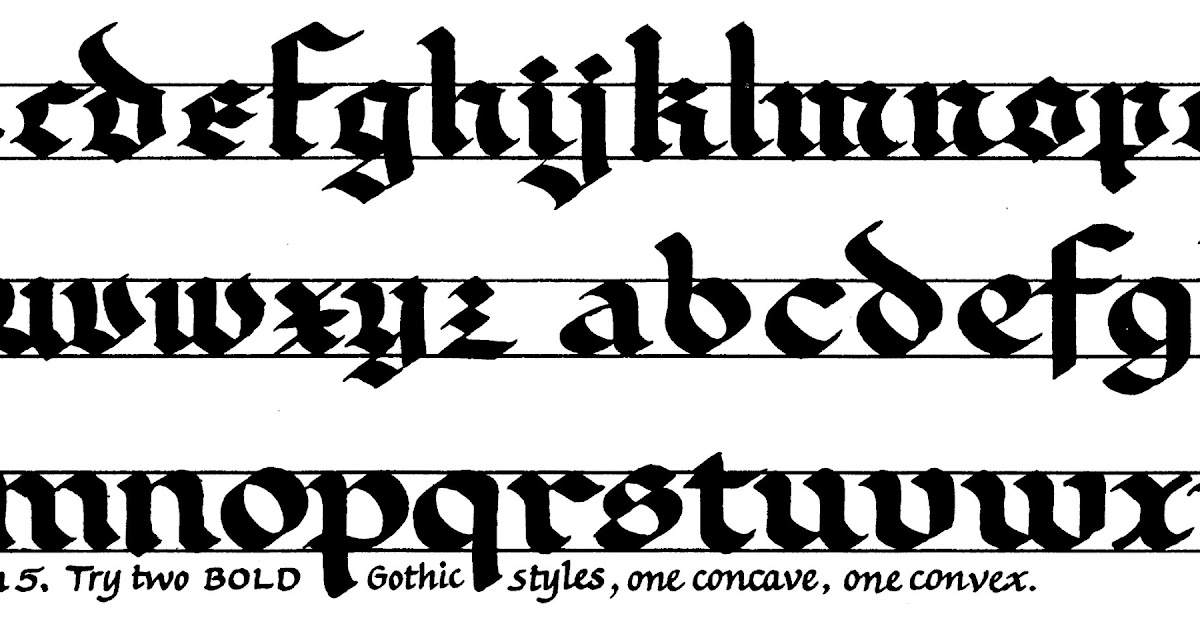
Очень хорошо, если у вас в рабочем ящике будет хранить¬
ся целый набор качественных кистей. Если ухаживать за ки¬
стями должным образом, они прослужат вам не один год.
Наиболее часто в каллиграфии используются кисти № 4, 3,
2, 1,0, 00 и 000.
Для того чтобы писать очень крупные буквы или сделать
надпись свободным курсивным шрифтом, вам потребуется
лей подойдет мягкая, упругая кисть с кончиком 6,5 мм из
конского волоса. Такой кистью удобно, например, писать
гуашью плакаты или с помощью специальных красок делать
декоративные надписи на ткани. Попробуйте написать кис¬
тью предложенные ниже упражнения — вначале отдельные
штрихи, а затем буквы целиком. Кисть при этом вы можете
держать так же, как держите ручку.
Самые дорогие, но и самые качественные — это колонко¬
вые кисти. Они хороши для любых работ, в том числе для
того, чтобы иллюминировать текст или написать его рим¬
скими буквами в изящном, легком версальском стиле.
полнение предлагаемых ниже упражнений поможет вам
увереннее чувствовать себя в работе с кистью.
íifutjjf))) укѣ С Ѣ
Начните с простых изгибов, внимательно следя за тем, чтобы в каждом штрихе Затем напишите полностью эти буквы, состоящие
отчетливо различались тонкая и толстая часть линии из только что освоенных вами штрихов
ТЕХНИКА
Изучение каллиграфии Blackletter (готика) для начинающих + Практические руководства
Начало работы с любым новым хобби/навыком
Во-первых, я чувствую, что существуют воображаемые барьеры для начала новых увлечений. Будь то обучение игре на гитаре, посещение тренажерного зала или каллиграфия, эти барьеры мешают некоторым людям даже начать. Думаю тут 2 вещи, боязнь сосать и незнание темы. Теперь я не могу избавиться от страха сосать, потому что, конечно, когда кто-то что-то начинает, у него ничего не выйдет. (Посмотрите сами на мои ранние посты в Instagram (@richardwideman).
Содержание
(Это было после многих попыток и многих часов практики) Даааа.
. Это учит всех нас тому, что все с чего-то начинают! А если серьезно, если вы будете упорствовать и практиковаться, то обнаружите, что у вас довольно быстро получается. Я надеюсь с помощью этого поста мотивировать некоторых людей, которые, возможно, не изучили искусство каллиграфии. Я намерен избавиться от этих барьеров с помощью этого поста, предлагая 3 способа обучения для 3 разных людей!
А
Очень Краткая история черной каллиграфииПрежде чем мы начнем изучать черную каллиграфию, я думаю, было бы уместно узнать, где и когда появился этот стиль письма и кто его использовал. Если вы нетерпеливы и хотите прыгнуть, я не буду винить вас, просто прокрутите (или щелкните) мимо этого (очень маленького) раздела. Если вам интересно, продолжайте читать.
Во-первых, блэклеттер — это всеобъемлющий термин для стиля письма, который может называться готическим шрифтом, готическим миниатюрным шрифтом, текстурой и даже иногда «староанглийским». Кто-то скажет, что эти вторичные термины неверны, но это зависит от того, кого вы спросите.
Я считаю, что можно с уверенностью называть это любым из них, поскольку большинство людей поймут, о чем вы говорите. Эта группа шрифтов была впервые популяризирована благодаря использованию в одной из первых печатных книг, которой была Библия Гутенбурга. Впервые он был напечатан в Майнце, Германия, в 1455 году.
Стиль Blackletter — это особый стиль письма, который характеризуется очень толстыми и очень тонкими линиями, как показано ниже. Когда он впервые популяризировался, люди в 15 веке называли его «готическим». В то время слово «готика» было синонимом варварства. Это могло бы объяснить количество людей, которые делают татуировки с таким шрифтом. Тогда это было даже резко, и я могу согласиться, потому что я рассматривал татуировку с черным письмом.
Смесь Gothic и Fraktur Blackletter Calligraphy Если блеклеттер был человеком, каролингский минускул был бы его великим предком. Каролингский минускул был впервые разработан в Европе в 8 веке в качестве стандартного письма.
Стандартизация латинского алфавита упростила его понимание и сделала более удобочитаемым в разных регионах, где существовали разные стили письма. Этот сценарий был основой всех форм черного письма и объединял греческий, ирландский, латинский и, конечно же, английский язык. Эти сценарии использовались в монастырях для тиражирования религиозных текстов. Ниже небольшой пример того, что такое каролингский минускул.
В результате этой стандартизации четыре основные разновидности блэклеттера появились в основном во Франции, Германии и Англии между 15 и 16 веками. С тех пор было много подмножеств и вариаций этих 4, но все происходило из этих 4 сценариев.
Слева направо: Textura, Batarde, Fraktur и Rotunda.Инструменты, необходимые для каллиграфии Blackletter
1. Инструмент для письма Blackletter
Кое-что, что можно сделать с помощью параллельного пера Pilot Короче говоря, лучший инструмент для каллиграфии Blackletter — это параллельное перо Pilot. У меня есть все причины и множество примеров, изложенных в моем подробном обзоре.
Однако, если вы не хотите покупать инструменты для каллиграфии, пока не узнаете больше о каллиграфии Blackletter, у меня есть несколько видео по обучению каллиграфии Blackletter карандашами! Один внизу, остальные здесь.
2. Хорошая бумага для каллиграфии
Лучшая бумага для каллиграфии Blackletter — HP Premium 32. Если вы используете перо Pilot Parallel, оно может растекаться на менее плотной бумаге (например, на обычной бумаге для принтера). Однако, если вы учитесь карандашами, вы, очевидно, можете использовать любую бумагу, которую найдете.
Два способа изучения каллиграфии Blackletter онлайн
Обычно у меня есть три способа (например, мой пост Copperplate), но у меня пока нет доступного видеокурса Blackletter.
Следите за обновлениями.
1. Для стремящихся к самообучению – практические листы
Если вы настойчиво изучаете каллиграфию Blackletter и занимаетесь самообучением, то практические листы для вас. Это не просто старая тетрадь. Эти листы предлагают структурированную практику, обучая вас строительным блокам черной каллиграфии, а затем детализируя буквы 8 черных алфавитов штрих за штрихом. Эта рабочая тетрадь поможет вам быстро овладеть нужными навыками. Включает:
- Инструменты, которые вам понадобятся
- Знакомство с каллиграфией Blackletter
- Базовые и расширенные штрихи
- 5 правил расцвета
- Эти 8 начертаний: Fraktur, Rotunda, Textura, Batarde, Italics, Uncial, Roman и Neuland
В ПРОДАЖЕ СЕЙЧАС
2. Для тех, кто бережно тратит деньги – Учебное пособие в блоге
Ваши первые каллиграфические штрихи Blackletter
Отлично! Ты сделал это! И у вас есть ваш первый Pilot Parallel или какой-нибудь инструмент для каллиграфии и хорошая бумага.
Отвинтите серую часть с обратной стороны пера и вставьте запечатанный чернильный картридж в конец, противоположный лезвиям (может потребоваться небольшое усилие). Первое, что вы заметите при письме, это то, что под разными углами вы получите разную толщину линий. В зависимости от направления, в котором вы идете, вы можете получить немного разные формы, как показано на изображении ниже.
Дело в том, что с черными буквами нужно держать ручку под углом примерно 30-40 градусов. Если вы поместите кончик инструмента на верхнюю часть угла ниже, он должен быть на одном уровне с этой черной линией. Следя за тем, чтобы угол оставался постоянным, перемещайте перо, чтобы создать фигуры, показанные ниже. Как только вы сделаете эти два штриха, у вас будет большинство фигур, которые вы можете сделать с пилотом параллельно. Теперь дело только за тем, как вы их устроите!
Держите Pilot Parallel Pen под углом 40 градусовНаписание букв готической каллиграфии
a, b (верхний элемент), c и g (нижний элемент) Большинство шрифтов blackletter имеют некоторые рекомендации, показывающие высоту каждой буквы в зависимости от ширины острия пера.
Как вы можете видеть на картинке выше, есть несколько квадратов, которые были созданы с помощью параллельного пера Pilot. x-height обычно имеет высоту 5 ширин пера, высота верхнего выносного элемента составляет 2–3 ширины пера, а высота нижнего выносного элемента обычно составляет 2–3 ширины пера.
- x-высота: размер тела буквы, указанный в ширине пера
- По возрастанию: Часть буквы, которая поднимается выше x-высоты
- По убыванию: Часть буквы, которая опускается ниже x- height
Если вы держите перо под углом 40-45 градусов (как на предыдущем рисунке) и повторяете пути, как показано на рисунке выше, вы должны получить что-то похожее на это. Если это неясно, посмотрите видео ниже.
Учебные пособия по каллиграфии Blackletter
Видеоурок «Как научиться каллиграфии Blackletter для начинающих» (строчные буквы) Не расстраивайтесь, если что-то не выглядит идеально, если, конечно, это не заставляет вас продолжать практиковаться и совершенствоваться.
Это потому, что это все, что нужно, чтобы преуспеть в этом замечательном хобби.
Каллиграфические образцы алфавита
Это было сделано некоторое время назад, но вот пример готского алфавита. Попробуйте, и как только вы освоитесь, попробуйте алфавит Fraktur под ним. Удачи и приятной практики!
«Simple» BlackletterCustom «fraktur» AlphabetБЕСПЛАТНЫЕ тренировочные листы по готической каллиграфии
Чтобы загрузить БЕСПЛАТНЫЙ тренировочный лист по готической каллиграфии, перейдите к моему сообщению с тренировочным листом здесь:
Учебные листы по готическому стилю БЕСПЛАТНЫЕ тренировочные листы по готической каллиграфии Вы можете скачать и распечатать напишите его на хорошей бумаге и следуйте видео выше.
Если вы думаете, что разобрались с этим видео/алфавитом. Ознакомьтесь с другими бесплатными уроками по каллиграфии, которые я разместил на YouTube здесь.
Как заставить каллиграфию Blackletter расцветать
Честно говоря, я использую слово расцветающий для обозначения всего, что является штрихом, но не является буквой. Они могут добавить изюминку любой букве или просто заполнить пустое пространство (что я и делаю). Это одни из самых забавных вещей в каллиграфии, когда вы делаете их правильно. Это действительно может сделать или сломать часть, над которой вы работаете. Слишком много просто выглядит бесполезно, а слишком мало заставляет вас хотеть большего. Вам действительно захочется попрактиковаться в них, но, к сожалению, с ними нет тренировочного листа. Вот немного вдохновения, но я считаю, что каждая каллиграфия развивает свой собственный стиль процветания. Так что я пытаюсь сказать, что это эксперимент! Пробуйте разные формы, прыжки и завихрения, пока не найдете то, что вам действительно нравится.
Тогда практикуйте их!
Цветущая каллиграфия BlackletterРасцветка: декоративная плавная кривая в почерке или завитках
Как сделать каллиграммы Blackletter
Некоторые другие вещи, которые вы можете сделать, чтобы добавить вам каллиграфии черного письма, будут каллиграммы 90! Это метод расположения ваших букв или штрихов в макете, представляющем визуальный образ. У меня есть полное видео, демонстрирующее, что это такое и как их сделать!
Вот и все, ребята! Спасибо, что дочитали до конца! Надеюсь, вы нашли это полезным, если вы дали мне знать, чем это помогло вам в комментариях!
Также на любые вопросы или комментарии, обещаю, что отвечу!
Большое спасибо 🙂
-Richard
Blackletter/Gothic Calligraphy For Beginners (+ БЕСПЛАТНЫЕ рабочие листы)
Этот пост и фотографии в нем могут содержать партнерские ссылки.
Делиться заботой!
- Фейсбук
- Твиттер
Каллиграфия Blackletter — это один из многих шрифтов, созданных с помощью пера с широким краем, и мой друг Эдгар собирается поделиться с вами самыми основами и шаг за шагом, как приступить к работе.
Кроме того, Эдгар также подготовил БЕСПЛАТНЫХ тренировочных листов, включая заглавные и строчные буквы – но об этом позже!
Всем привет,Меня зовут Эдгар Вилла . Некоторые из вас могут знать меня по моей учетной записи в социальной сети «Сделано Эдгаром» , и я мексиканский каллиграф/художник из Джерси-Сити.
Я написал эту статью, чтобы помочь всем новичкам, заинтересованным в изучении каллиграфии Blackletter.
В этом учебном пособии вы узнаете об этих 6 вещах;- Origins of Blackletter
- Инструменты, необходимые для начала
- Как пользоваться инструментами для достижения наилучших результатов
- Как пользоваться рекомендациями для идеального письма каждый раз
- Понимание основных форм букв
- Основы расцвета
Начнем!
Origins of Blackletter Blackletter, также известный как «Готика», был создан в XII веке, когда все больше и больше людей начали читать и писать.
Спрос на книги рос, и их нужно было писать быстро, чтобы удовлетворить этот спрос.
Сжатый стиль письма Blackletter позволил разместить больше слов на одной странице и, следовательно, использовать меньше пергамента, что снизило производственные затраты.
Короче говоря, Blackletter упростил и удешевил производство большого количества книг.
Blackletter имеет множество вариаций Fraktur, Rotunda и Schwabacher, и это лишь некоторые из них. Поскольку в Blackletter имеется большое семейство скриптов, я сужу его и помогу вам понять основы скрипта, известного как « Textura Quadrata» .
Необходимые инструменты для каллиграфии BlackletterЧтобы научиться каллиграфии blackletter, вам понадобятся основные инструменты каллиграфии.
Однако ниже я дал свою собственную рекомендацию.
1. Береговое преимущество Nib
- Пилотные параллельные ручки — мои любимые, потому что они готовы к использованию из коробки
- Любое широкое преимущество
2.
Straight Holder
2.0005 3. Бумага, которая не растекается 4. Каллиграфия чернила 5. Вода и бумажное полотенце для чистки перьев 60062 60062
- Я использую «роликовую линейку» , потому что она помогает мне легко проводить ровные горизонтальные и вертикальные линии
- Обычная линейка подойдет так же хорошо
7.
Карандаши
- 4H-HB Карандаши рекомендуются , потому что любой более тяжелый графит затрудняет стирание
8.eraser
- . Размещенная эразера , но любой Eraser. выберите для ваших вопросов каллиграфии!
С самого первого дня я использовал бумагу Rhodia, вот две веские причины, почему вы должны делать то же самое;
- Чернила не растекаются
- У вас есть возможность сделать бумагу разлинованной или пунктирной, что упрощает создание прямых линий, необходимых для Blackletter
Для любого произведения, которое я повешу на стену, я буду использовать лучшую бумагу, которую смогу достать
Но для практики подойдет любая бумага низкого качества.
Как пользоваться инструментами для каллиграфииКак и у любого инструмента, будь то работа по дереву или скульптура, у каждого инструмента есть цель, и есть способы максимизировать эффективность каждого инструмента.
Широкое перо
Если вы используете широкое перо, возможно, вам потребуется «подготовить перо» перед тем, как вы им воспользуетесь.
При покупке нового пера на него наносится защитное покрытие , которое предохраняет перо от ржавчины при хранении. Это защитное покрытие, хотя и важное, работает против вас, когда вы опускаете перо в чернила.
Если вы не подготовите перо к письму, чернила не будут должным образом прилипать к перу. У вас также будут чернильные капли, когда вы будете писать, или вам придется повторно обмакивать перо каждые несколько штрихов.
Вот 4 способа «Подготовить перо»:- Очистите наконечник зубной щеткой и зубной пастой под теплой водой
- ОСТОРОЖНО воткните наконечник в картофель на несколько минут
- Смочите наконечник слюной и протрите его бумажными полотенцами
- Поместите наконечник на свет пламя
- Использование огня очень опасно, и я не несу ответственности за любой вред, причиненный вам или другим.
Соблюдайте осторожность и будьте очень осторожны. Этот метод также может испортить перо, если оставить его слишком долго над пламенем. Не рекомендую новичкам. Попробуйте на свой страх и риск .
Существует два способа загрузки чернил в широкое перо: либо обмакнуть перо в чернила, либо заполнить резервуар с помощью кисти.
*Некоторые широкие перья не поставляются с резервуарами, и для достижения наилучших результатов их необходимо окунать
Если вы окунаете перо, убедитесь, что излишки чернил с него вытекают обратно в бутылочку с чернилами. Если на перо слишком много чернил, оно будет капать при нанесении штрихов.
Кроме того, небольшое количество чернил заставит вас окунать перо в чернила каждые несколько движений.
Если чернила на наконечнике начинают высыхать и превращаться в липкую массу, обязательно промойте наконечник водой и тряпкой, чтобы удалить засохшие чернила.
Вы также можете снять резервуар для более глубокой очистки пера.
Pilot Parallel Pen
* снимите резервуар ОСТОРОЖНО, потому что он ОЧЕНЬ ХРУПКИЙ, а также, чтобы не сломать резервуар, вы можете добраться до труднодоступных мест зубной щеткой *Эта ручка готова к использованию и удобна для начинающих. Главный совет по использованию этой ручки — применять равномерное давление, чтобы получить наилучшие результаты. Слишком сильное давление на левую сторону сделает правую сторону гребка прерывистой, и наоборот.
Я настоятельно рекомендую использовать ТОЛЬКО картриджи марки Pilot.
При замене чернильного картриджа убедитесь, что вы чистите перо, чтобы предыдущий цвет чернил не смешивался с новым и не давал цвет, который вам может не понравиться.
Начнем! – НаправляющиеКогда я начинаю новый проект, я буду использовать направляющие даже на этапе эскиза. Направляющие помогают мне держать все мои буквы ровными и последовательными.
Textura Quadrata обычно требует 4-5 ширины пера для высоты x и 6-7 ширины пера для верхних и нижних элементов.
Я правлю горизонтальные линии, чтобы буквы оставались одинаковой высоты, и правлю вертикальные линии, чтобы мои вертикальные штрихи были как можно более прямыми.
Не бойтесь пробовать что-то новое
Вам не нужно придерживаться ширины между 4 и 6 перьями, смешивать их и пробовать разные веса букв.
Помните, что правила созданы для того, чтобы их нарушать.
Понимание основных форм букв и интерваловЕсли вы посмотрите на любую рукопись, написанную в Textura Quadrata, вы заметите плотные и тяжелые штрихи, придающие ей общее ощущение темности.
Прямые вертикальные линии и небольшие промежутки — вот что придает Textura Quadrata уникальный стиль.
Выделите время, чтобы попрактиковаться в написании вертикальных линий и ромбовидных засечек.
Практика ведет к совершенствуНе расстраивайтесь, если некоторые из ваших гребков будут не такими прямыми, как вам хотелось бы.
Не торопитесь и помните, что с практикой ваши удары улучшатся.Начните с простых букв: b,c,e,f,h,i,j,l,o,p,q,r,t,u
Затем перейдите к более сложным буквам: a,d,g,k,m,n,s,v,w,x,y,z
Угол, под которым написана Textura Quadrata, варьируется от 40 до 45 градусов.
Интервал между буквами ВАЖЕНМежду каждой буквой должно быть пространство шириной не менее одного пера
и пространство шириной в один кончик внутри букв, также известное как «счетчик».
Расстояние между словами должно составлять 2 ширины пера.
Придайте стиль своим письмамКак только вы освоите основы, вы можете постепенно придавать своим письмам стиль. Вы можете добавить к зажимам то, что я называю «шипами». Это можно сделать с помощью края пера.
Вы можете сделать шипы полными и тяжелыми
Или сделать шипы толщиной с волос, решать вам.
Вы можете добавить несколько завитушек к своим зажимам.
Шаг за шагом
После того, как вы научитесь составлять буквы, вы сможете начать манипулировать своими буквами и расширять свои завитки. Со временем вы создадите идеальные буквы и сбалансированные завитушки.
Будьте ОЧЕНЬ осторожны с этим ластикомКогда я закончу и чернила высохнут на 100%, я аккуратно сотру линии. Я обнаружил, что с помощью ластика-клячки можно легко стереть направляющие.
Всегда помните, что при использовании ластика нужно быть очень осторожным с любыми чернилами, даже если они выглядят совершенно сухими.
Не забудьте убраться, когда закончите. Вы не хотите возвращаться к перу с засохшими чернилами, поэтому очищайте его после каждого использования.
Ошибки делают вас великимЯ не могу сказать вам, сколько раз я ошибался в слове или наносил слишком много чернил на перо, что оставляло большую каплю, приходилось начинать с самого начала. Это случается с лучшими из нас, так что пусть это вас не останавливает.
Учась на своих ошибках, вы сможете вырасти и стать отличным каллиграфом.
Подходит ли вам Blackletter?Посмотреть эту публикацию в Instagram
Сообщение, опубликованное Made by Edgar (@made.by.edgar)
Если ваш ответ «да», вы можете продолжить совершенствовать свои навыки, загрузив мое БЕСПЛАТНОЕ учебное пособие. Это поможет вам сформировать основные формы букв для шрифта Blackletter Textura Quadrata.
Если ваш ответ отрицательный, я все же предлагаю вам скачать его и попробовать. Возможно, это станет началом нового интересного хобби.
Не стесняйтесь писать мне в Instagram, если у вас есть какие-либо вопросы. Я всегда стараюсь помочь и ответить каждому. Также, если у меня нет ответа на вопрос, я постараюсь указать вам правильное направление.
Большое спасибо за то, что нашли время, чтобы прочитать мой учебник по Blackletter, и я надеюсь, что вы нашли его полезным.
Оставьте свой адрес электронной почты ниже, следуйте инструкциям и получите доступ к рабочим листам. Будьте в курсе моих руководств и получите мгновенный доступ к ящику для надписей – Растущая библиотека бесплатных ресурсов для надписей и каллиграфии, которая включает в себя – БЕСПЛАТНО загружаемых практических листов, кисти Procreate, 30-дневный планировщик надписей, печатные формы и многое другое!Вы также сможете загрузить все остальные рабочие листы (и бесплатные), доступные в настоящее время в Lettering Crate.